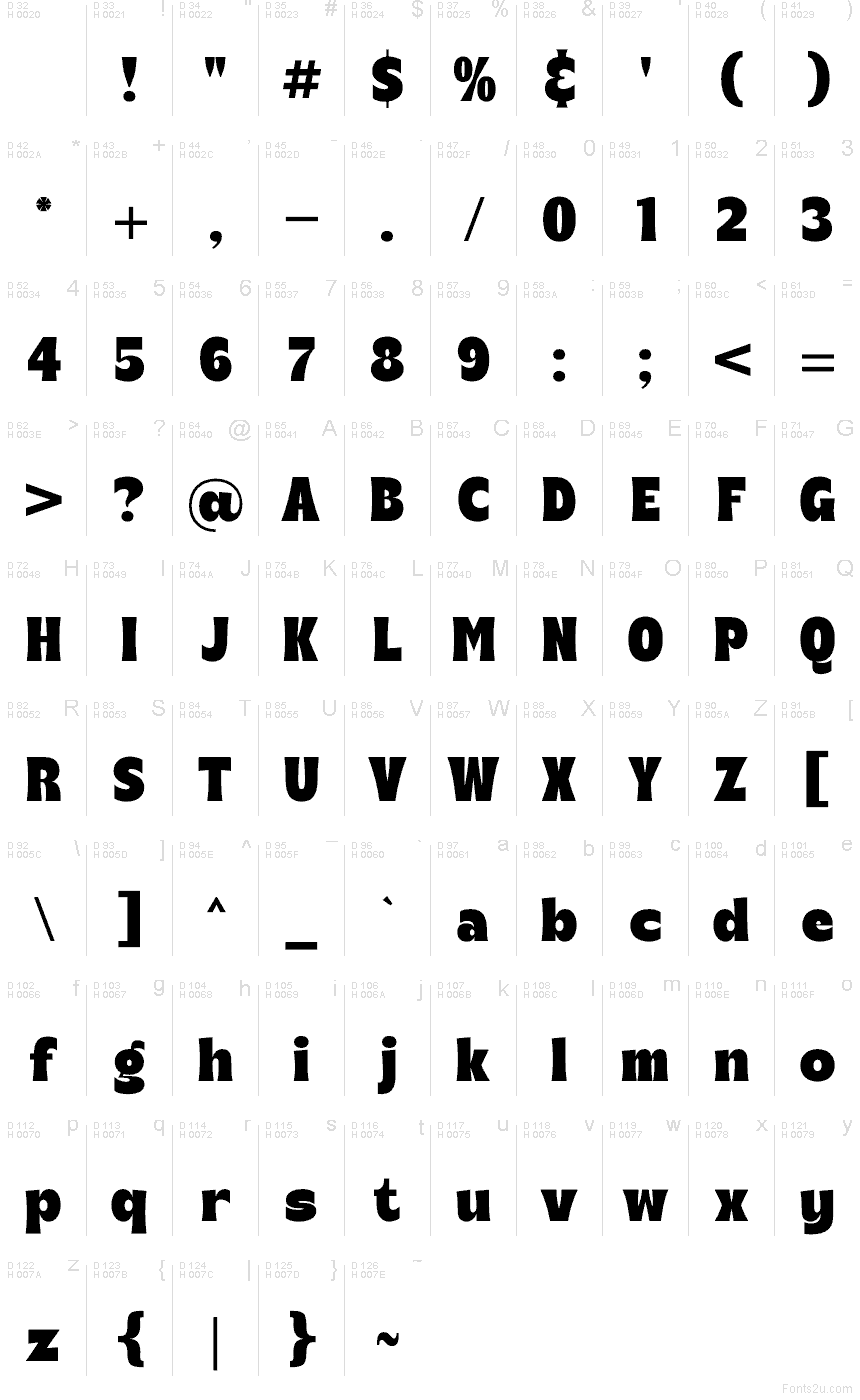
Mistur Sleuth od Timeless Type je bezplatné bezpatkové retro písmo. Jeho hutné, masivní tvary přecházejí od vysokých úzkých liter k širokým zaobleným formám, přičemž nerovné spoje a zjemněné rohy připomínají uvolněné, ručně vyřezávané plakátové nápisy ze 70. let.
Značky spojené s prodejnami desek, vintage módou nebo nezávislými obaly potravin mohou jeho nahuštěnou siluetu využít k navození dojmu ručně malovaných vývěsních štítů a nízkorozpočtové koncertní grafiky, aniž by doslovně napodobovaly styl konkrétní éry. Skvěle se hodí také na hudební plakáty a obálky časopisů určené čtenářům, které oslovuje hravá kontrakulturní grafika, protože proměnlivá šířka písmen dodává i důvěrně známým slovům vzhled originálního nápisu z výlohy v nějaké staré čtvrti.